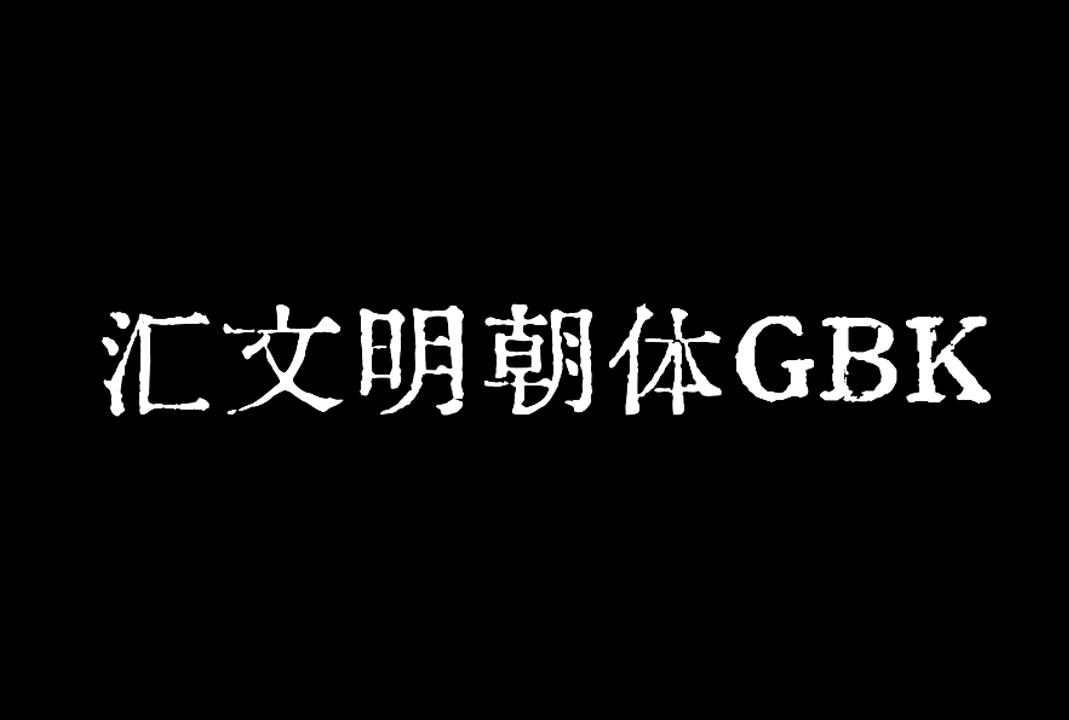
汇文明朝体GBK(Huiwen-mincho Regular)是一款由网友特里王发布的一款免费商用的中文复古印刷字体,该字体为汇文系列(仿楷黑明)之明朝体。
汇文明朝体GBK(Huiwen-mincho Regular)的字形主要来自五六十年代官方各种汉字改革文件。简体字部分基本复原五六十年代书籍印刷样貌。繁体字、传承字部分基本还原民国至共和国初期字形样貌。是比较原滋原味的旧铅字印刷风格。